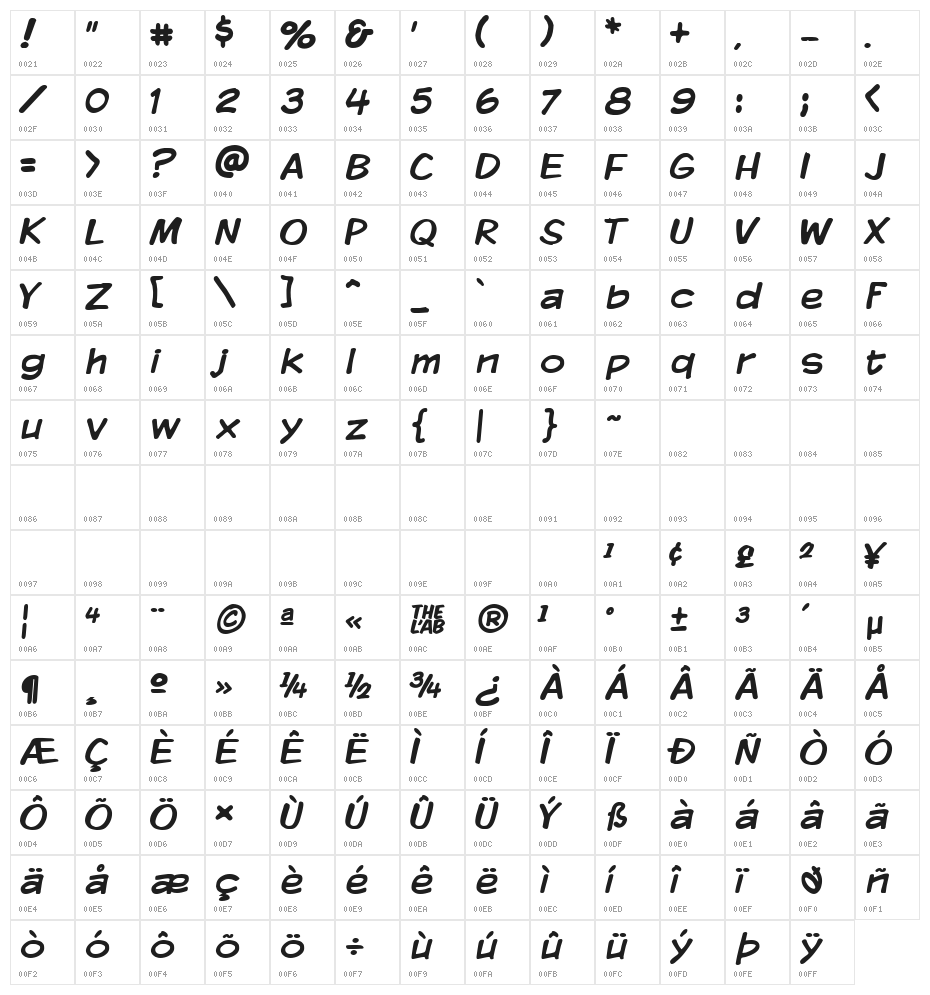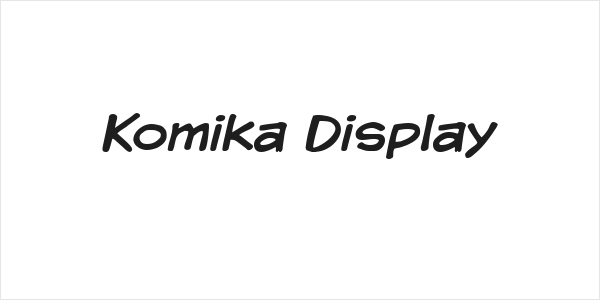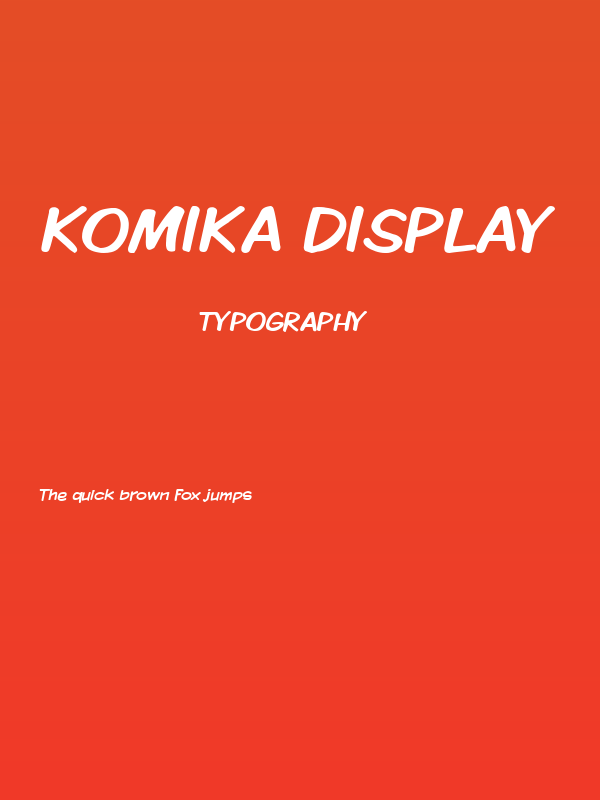
Komika Display Font
| Gesamtstil | Playful, Comic |
| Anwendungsfall | Headlines, Posters, Branding |
| Vorgeschlagene Projekte | Ideal for comic books, children's books, playful branding, and casual posters. |